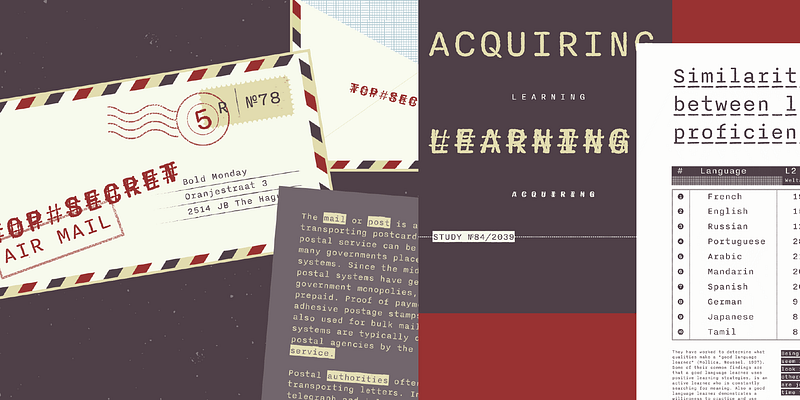
Nitti Typewriter forma parte de la suite ampliada Nitti de Bold Monday, inspirada en las sans serifs más antiguas conocidas: las grots idiosincrásicas ingleses del siglo XIX. Los cinco estilos de la familia (Normal, Abierta, Subrayada, Corregida y Cameo) rinden homenaje a la estética de las máquinas de escribir, que combinan la precisión mecánica con los fallos y reparaciones humanas. Nitti Typewriter ofrece un amplio soporte de idiomas, y sus formas de letras tienen un aspecto orgánico ligeramente desgastado, como si estuviera desgastado por el uso repetido. Bold Monday, 2009–2016.